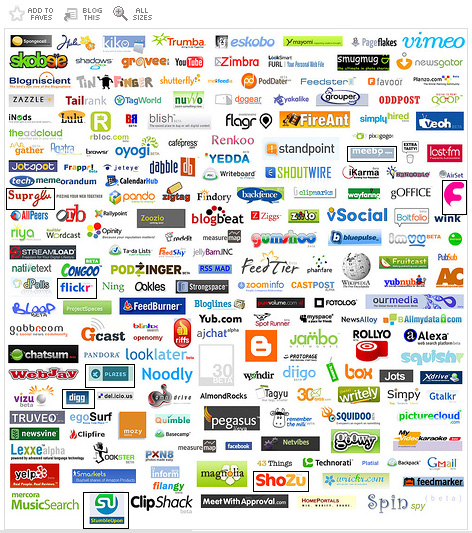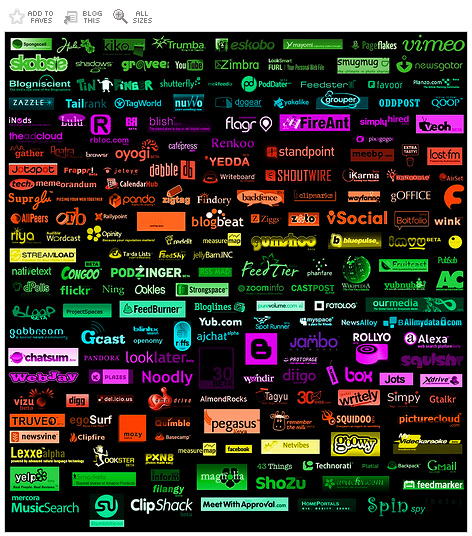
Die neue Logo-GenerationDer Berliner Designer und Fotograf Ludwig Gatzke (30; User-Name
»Stabilo-Boss«) hat auf flickr einen Logo-Friedhof mit den
Firmenzeichen der neuen Web-2.0-Unternehmen veröffentlicht, der weltweit
zitiert wird. Boingboing schreibt: »Sehr beeindruckend
... erinnert irgendwie an die tausend Swooshs jener Unternehmen, die
während der Dotcom-Blase die Loft-Etagen bevölkerten.« Andere
flickr-User steuern weitere Wortmarken bei, rufen zum Überarbeiten auf oder
kolorieren das Poster um. Weiterlesen ...
Die Kommentare zu der Logo-Übersicht offenbaren Spott, Bewunderung,
Verwunderung ...
Und Selbstironie. Wycliff fragt: Was kennzeichnet eigentlich Web-2.0-Anwendungen? Er weiß die Antwort: 1. Endlose Beta-Phase 2. abgerundete Ecken 3. Gigantische Schriften 4. Ajax (Asynchronous Javascript and XML) 5. Checkbox-Icons 6. überall RSS-Feeds 7. Tags 8. »Sozial- ...« 9. AdSense-support 10. Google-Maps-Integration Winona vermisst das Skype-Logo. Chuck Fletscher nominiert Mologogo.com. Yaaron ergänzt die Web-2.0-Merkmalliste um Punkt 11.: Oranges oder grünes Logo ![]() Die Logo-Collage von Stabilo-Boss alias Ludwig Gatzke, in verschiedenen Größen bei flickr zu finden Der Japanische flickr-User Otsune hat den Logo-Grabstein auf seine Art weiter verarbeitet: ![]() Logo 2.0 [Stabilo Boss on Flickr]